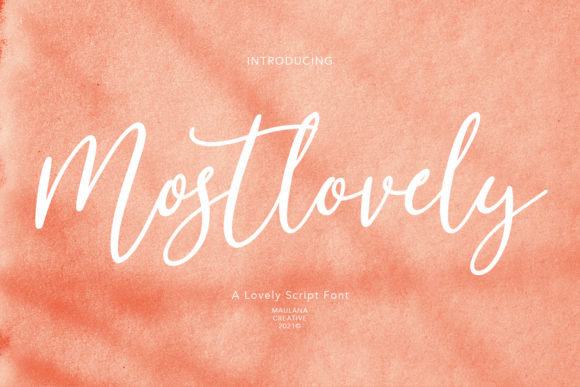
Creativefabrica Mostlovely Font
[Creativefabrica] Mostlovely Font
Mostlovely - романтичный и милый каллиграфический шрифт с символами, которые танцуют вдоль базовой линии.
Он добавит роскошную искру в любой дизайнерский проект, который вы хотите создать!